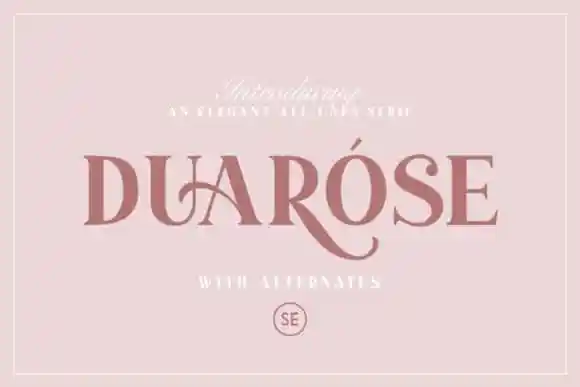
A fonte Duarose Serif é uma elegante tipografia serifada que incorpora elementos clássicos e simplicidade, feita pelo designer Saridezra. Seu design atinge um equilíbrio entre sofisticação e facilidade de leitura, criando uma paleta versátil de alternativas para cada caractere que podem transformar apresentações ou logotipos em verdadeiros trabalhos de arte. Duarose oferece múltiplas opções linguísticas e está já PUA Encodificado, garantindo mais flexibilidade no uso da sua fonte. Além disso, o suporte a idiomas multi-língue dá à Duarose Serif um valor incomparável para designers que trabalham com múltiplos países. A combinação de estilo elegante e alternativas únicas oferece uma solução perfeita para aquelas necessidades onde você precisa garantir que sua mensagem seja não só legível, mas também impactante. Seja em design gráfico, publicidade ou criação de logotípicos, Duarose Serif é a escolha ideal para aqueles buscando apresentações memoráveis e ressaltadoras no mercado.